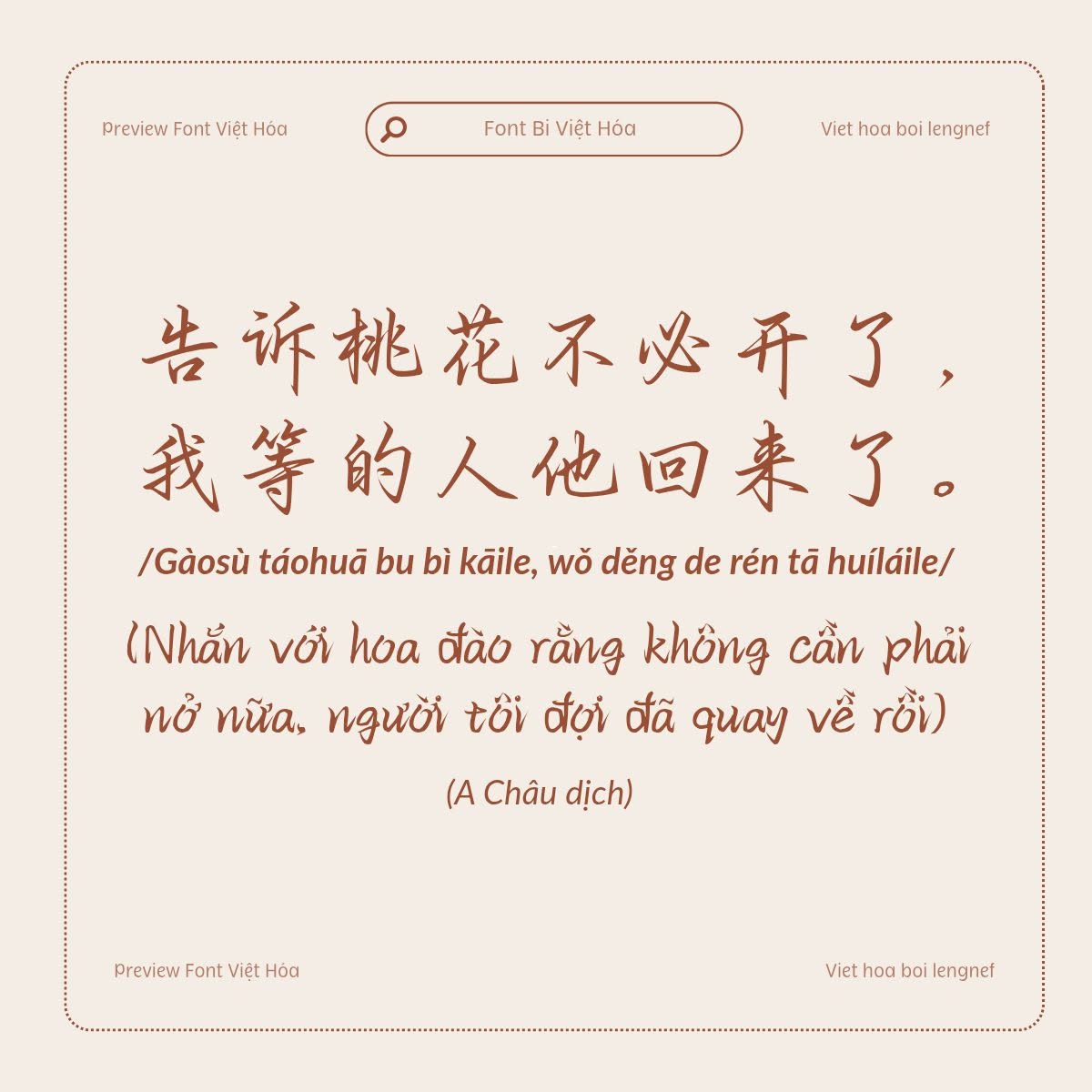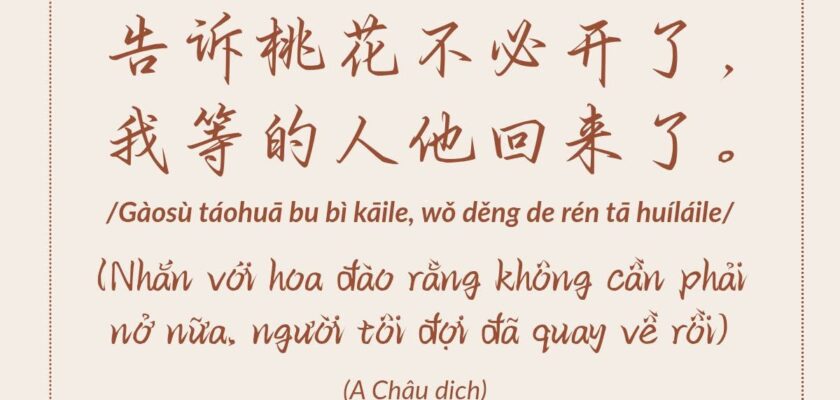
Share Font 74 || LF Bi
Bǐ (笔) trong tiếng Trung nghĩa là bút. Được tạo bởi những nét viết tay nguệch ngoạc. Chính vì ko theo bất cứ nguyên tắc nào làm cho phông chữ trông tự nhiên hơn.